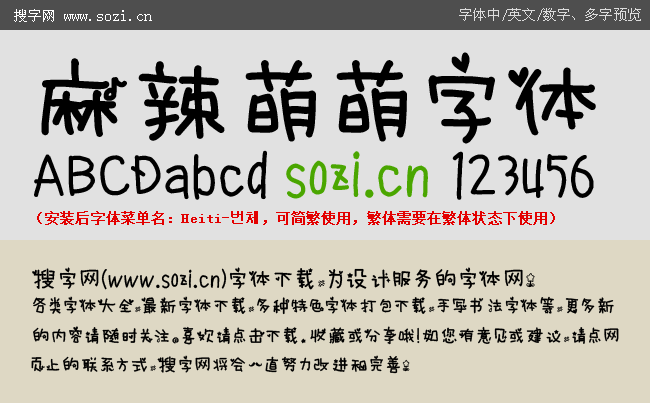
麻辣萌萌字體
搜字網(wǎng)給大家提供一款卡通手寫風(fēng)格的手機中文字體下載。名字叫麻辣萌萌字體,這款手機字體是仿照兒童手寫風(fēng)格的卡通手寫字體,結(jié)構(gòu)帶有POP字體風(fēng)格,字體間還插入有趣的卡通圖案,特別適合喜歡手機字體個性一些的朋友在手機上安裝使用。